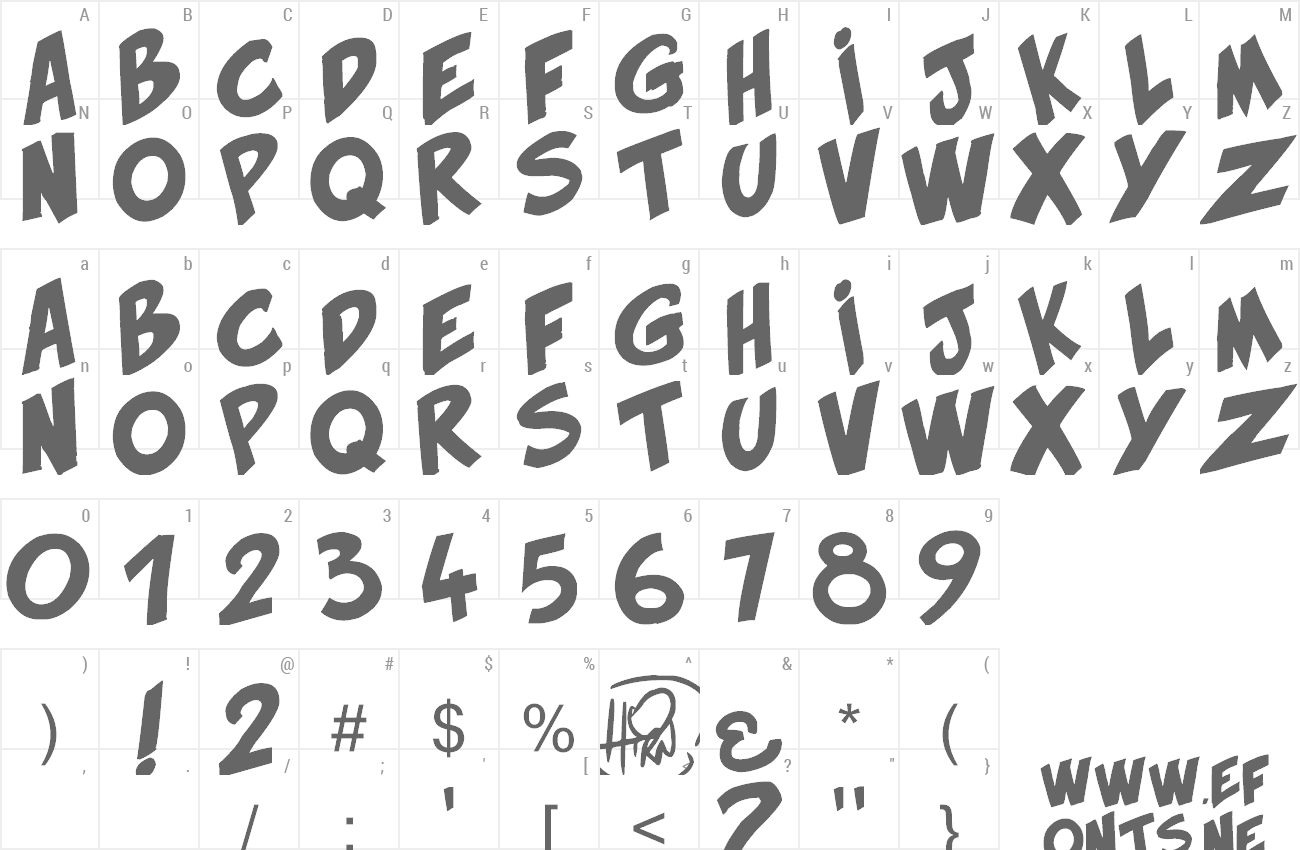
| Font name: | Hirn Bold |
| Author: | Laurent Hirn |
| Note by Laurent Hirn | |
Typo onomatopée bd réaliste. Définir l'approche à -100 pour l'effet escompté. |